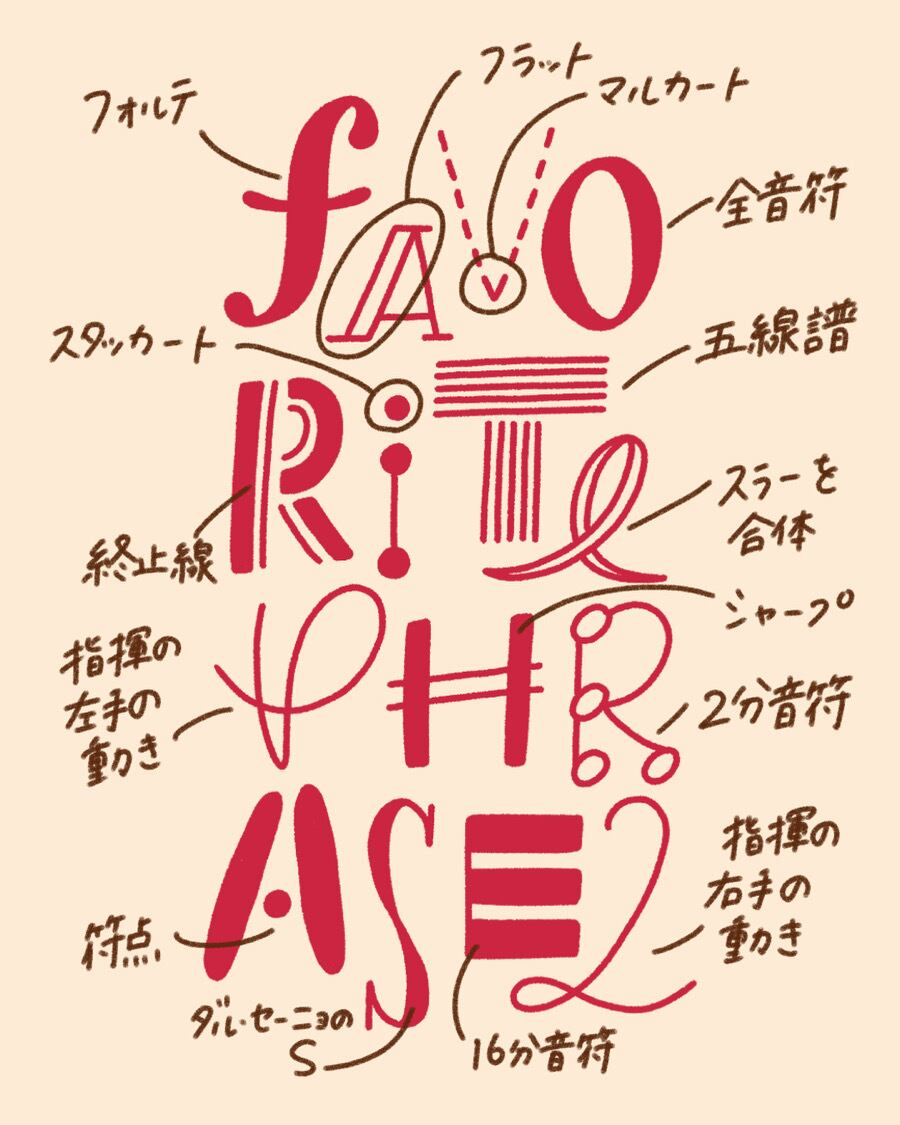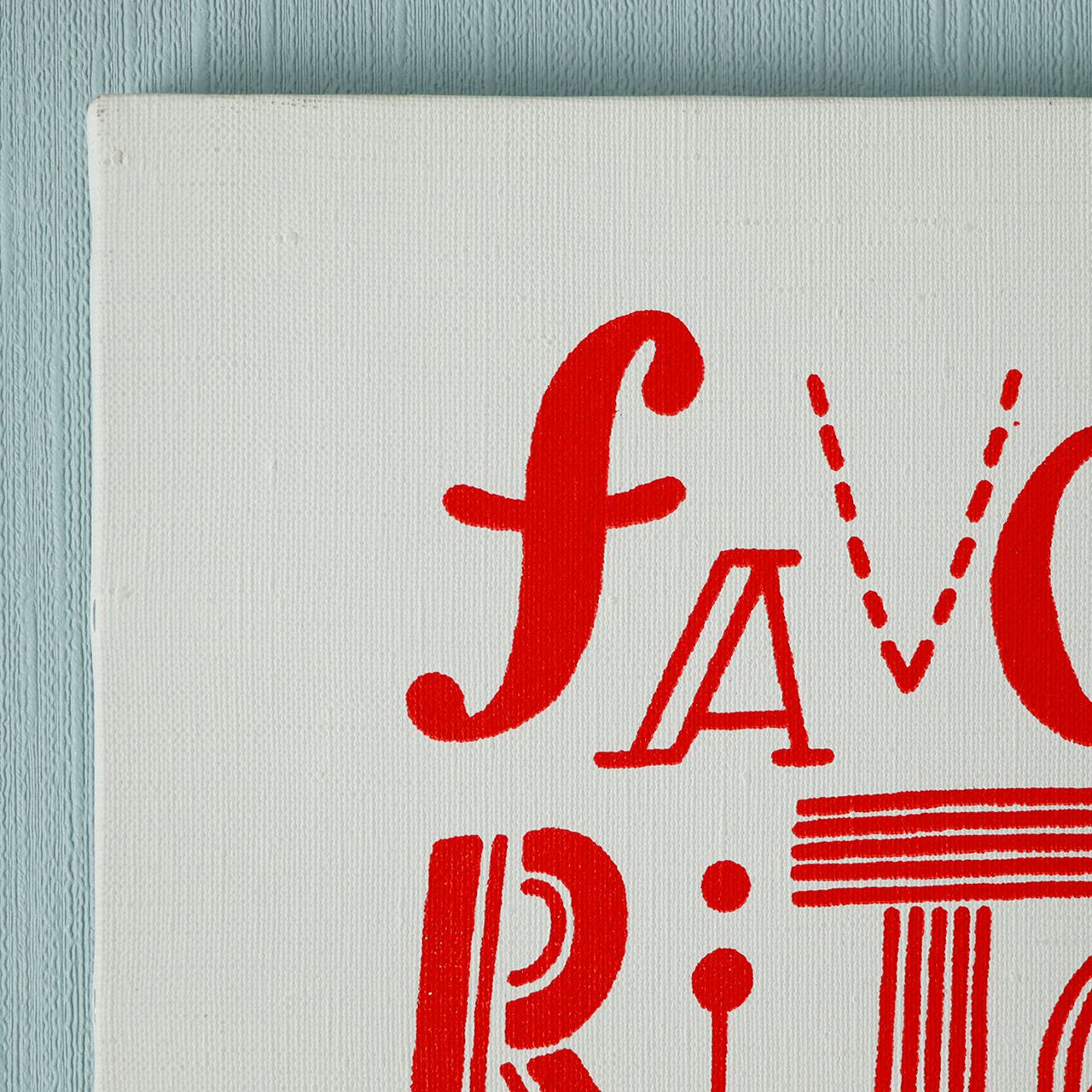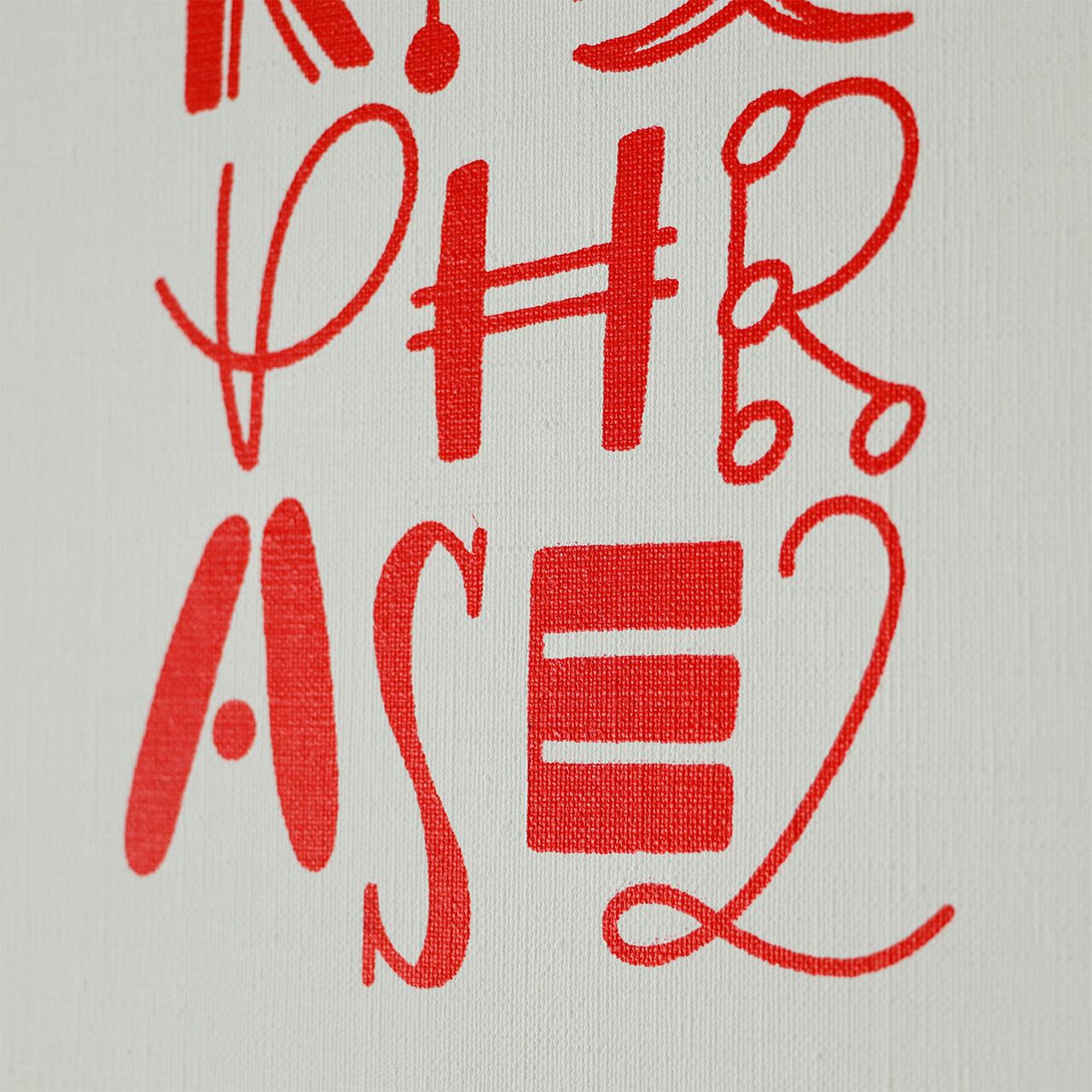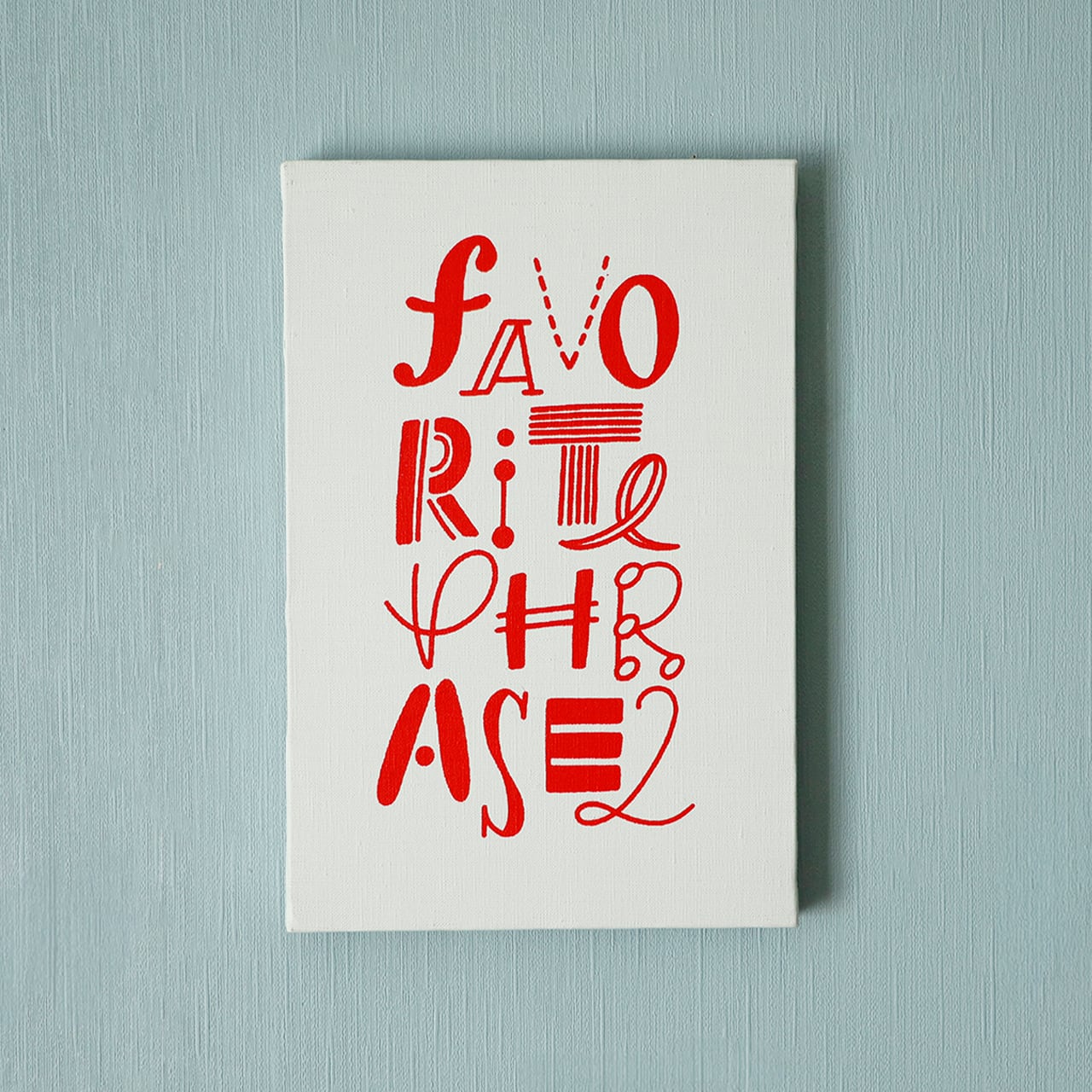
favorite phrase2(シルクスクリーン)
favorite phrase2
2026年4月に開催した個展「favorite phrase2」のメインビジュアルを
キャンバスにシルクスクリーン印刷した作品です。
全フォント、音楽と楽譜をモチーフにしたものになっています。
音楽やってる方、ぜひ答え合わせしてみてください♪